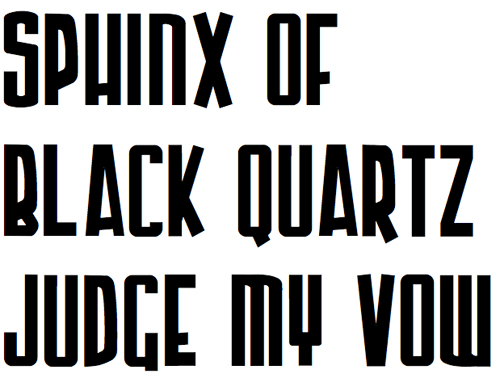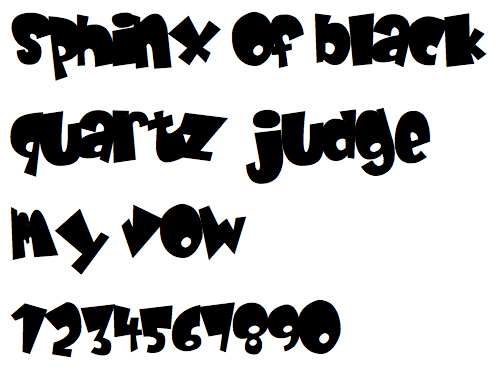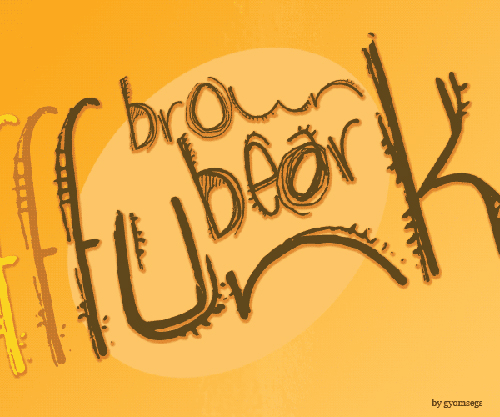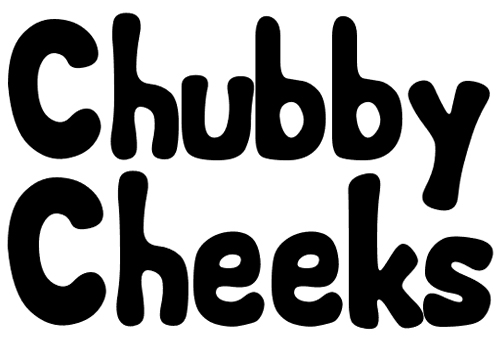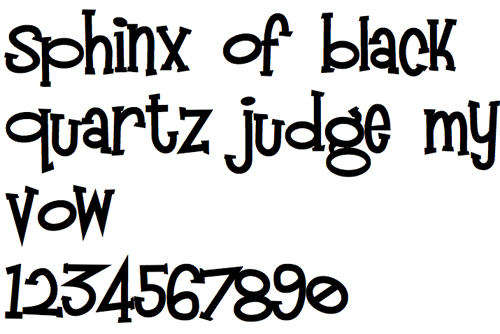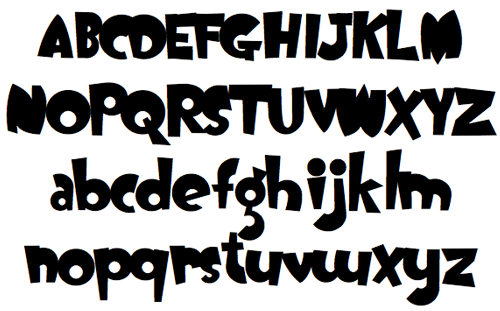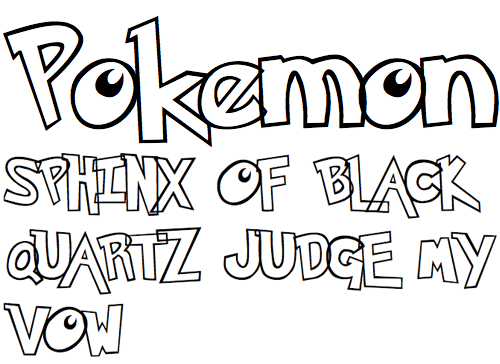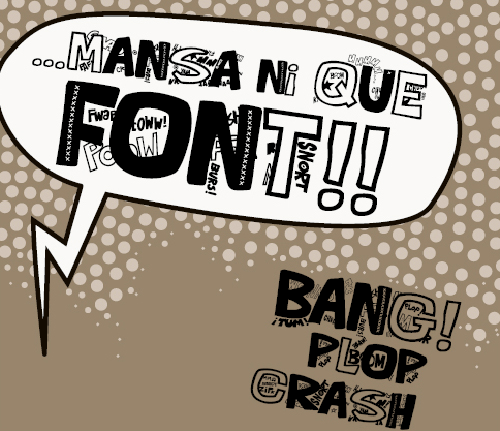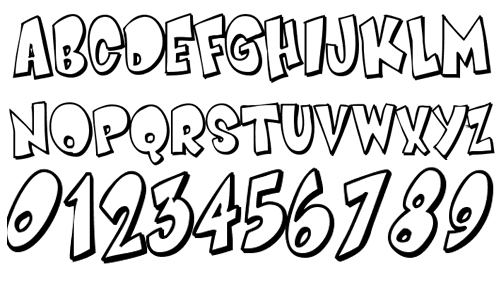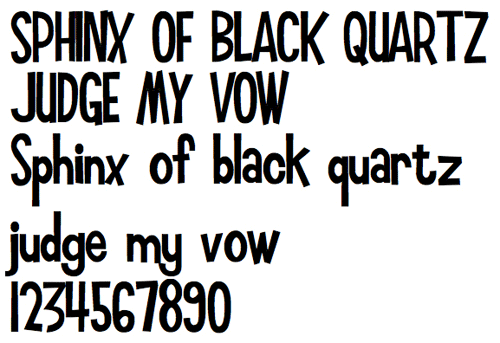
40 бесплатных мультипликационных шрифтов
40-мультипликационных-шрифтовВозможно, вы один из тех, кто считает что обычные шрифты для ваших работ слишком скучны и обычны? Почему бы вам тогда не украсить свои работы шрифтами, которые будут смотреться стильно и весело? В наше время мультипликационные шрифты очень популярны.
В этой подборке вы сможете найти 40 таких забавных и необычных шрифтов. Все эти шрифты бесплатны и вы без труда сможете загрузить их перейдя по ссылке над выбранным вами примером.
Шрифт под названием Que FONTita!
мультипликационные шрифты
Шрифт Burrito
шрифты с узорами
Жирный дутый шрифт Oogie Boogie
Жирный дутый шрифт
Контурный шрифт Pokemon
Контурный шрифт
Забавный иллюстрированный шрифт Clink Clank
Забавный иллюстрированный шрифт
Иллюстрированный шрифт Denne’s Aliens
Иллюстрированный шрифт
Шрифт Fighting Spirit
бесплатные иллюстрированные шрифты
Жирный шрифт Armor Piercing
Жирный шрифт
Шрифт с глазами Eyesis
Шрифт с глазами
Фигурный шрифт akaHoggle
Фигурный шрифт
Полный шрифт Altamonte
Полный шрифт
Искривленный шрифт BabOonjaZzbaSsoOn
Искривленный шрифт
Шрифт с колючками Cactus Sandwich
Шрифт с колючками
Космический шрифт Cosmic Dude
Космический шрифт
Полосатый шрифт Candy Time
Полосатый шрифт
Шрифт Chubby Cheeks
Веселый шрифт
Шрифт-зарисовки Gwibble
Шрифт-зарисовки
Шрифт с иллюстрациями LoOse Gangster
Шрифт с иллюстрациями
Шрифт Chlorinar
Шрифт с прожилками
Пятнистый шрифт Army Beans
Пятнистый шрифт